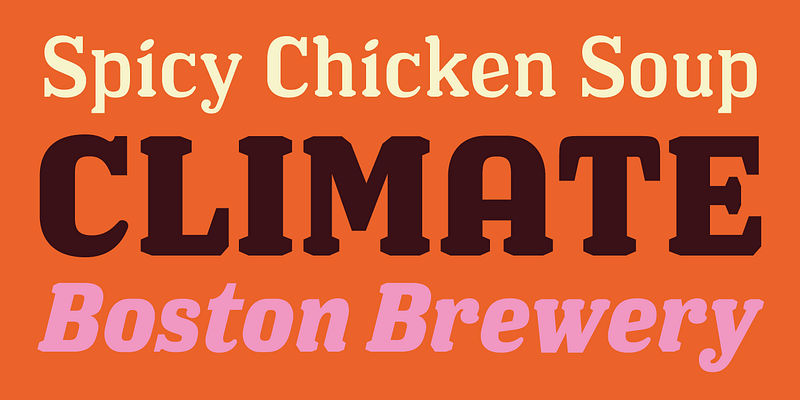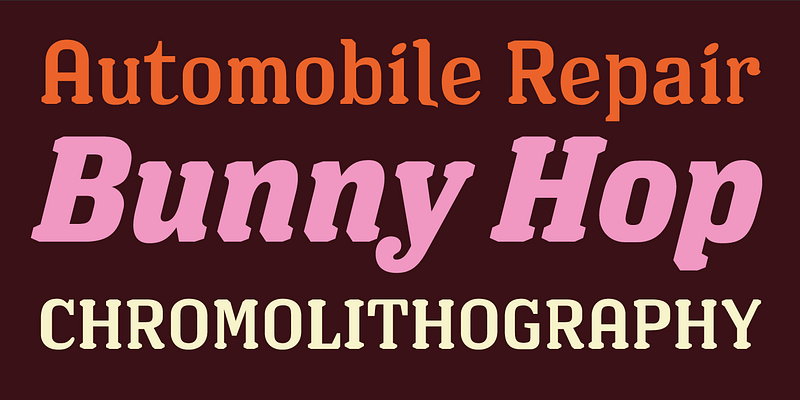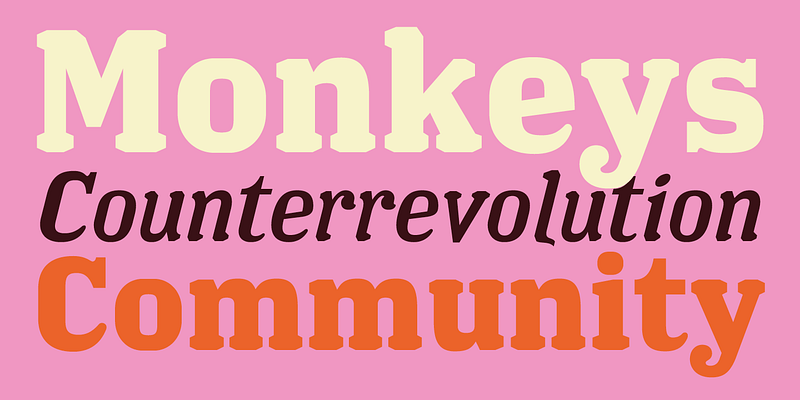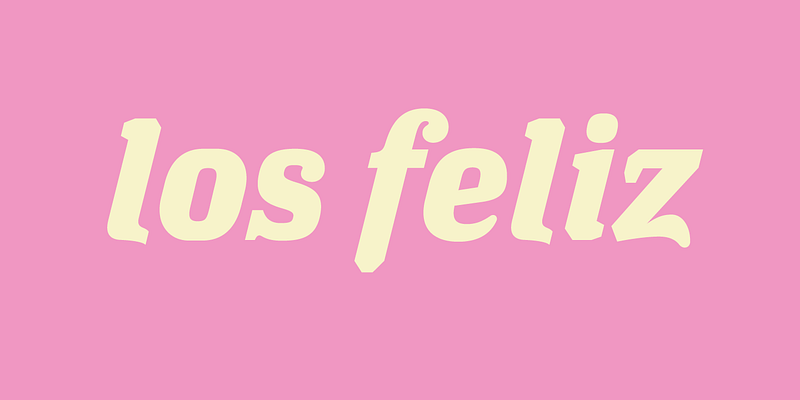
今日のデザイナーは、70 年代と同様、Helvetica をはじめとする味気のないサンセリフ書体を好んで使用します。これらのフォントは、超然としたスタイルで印刷物をプロらしい印象に仕上げ、それが今、とてもクールだと考えられています。
「Los Feliz」は、このトレンドとは正反対です。「Los Feliz」の文字を 1 つひとつ見ると、凸凹ばかりが目立ち、書体を描くことの難しさを感じさせます。小さな不具合が気になって、完璧な文字を描くのは困難だと感じます。しかし、「Los Feliz」を文字組みしてみると、そのような凸凹はほとんど消えてしまいます。明らかにこの書体は、正しいデザインという概念を破壊できる人、完全にコントロールできているのに、そうでないかのように見せる方法をよく知っている人が描いたものです。